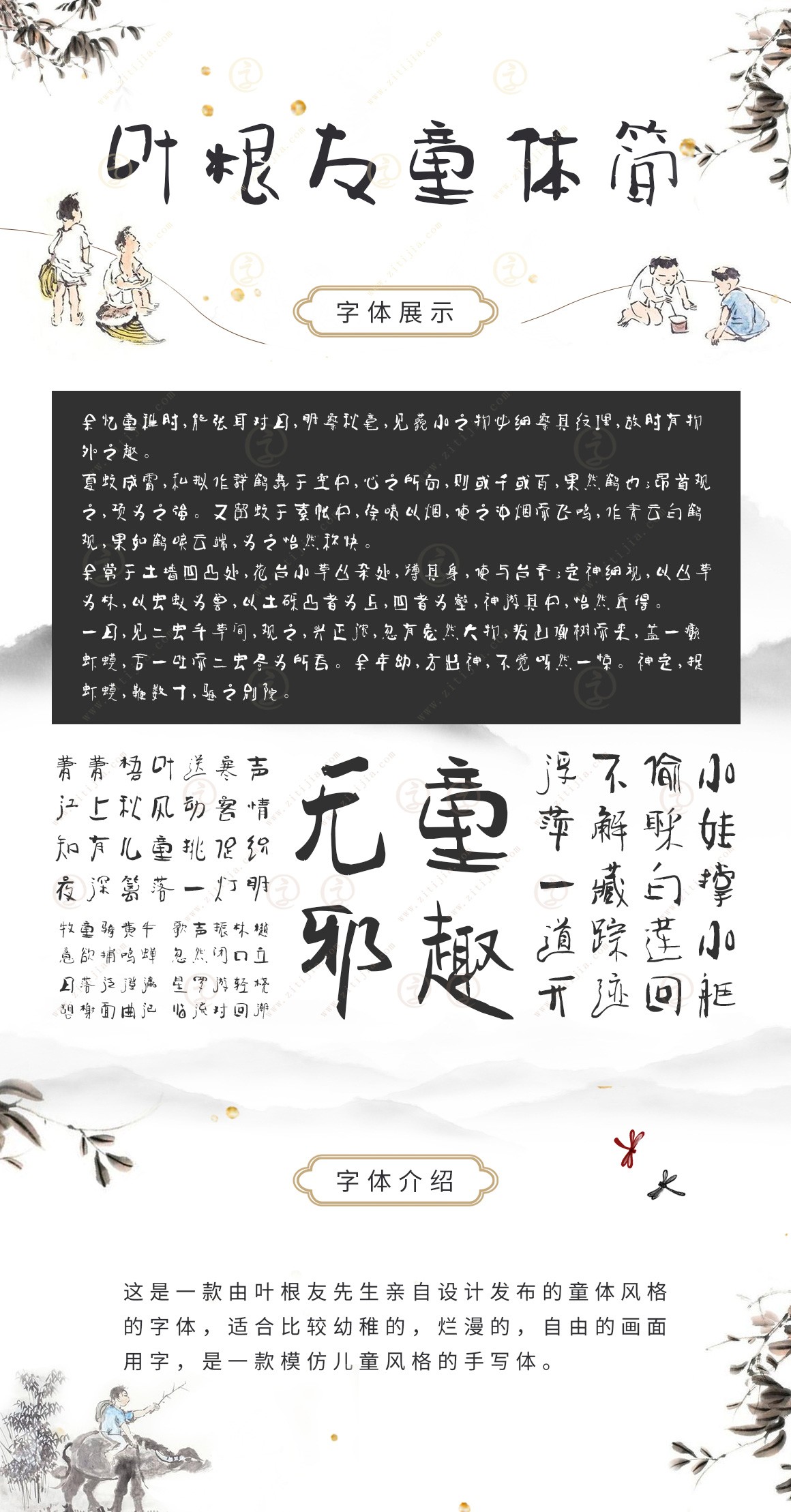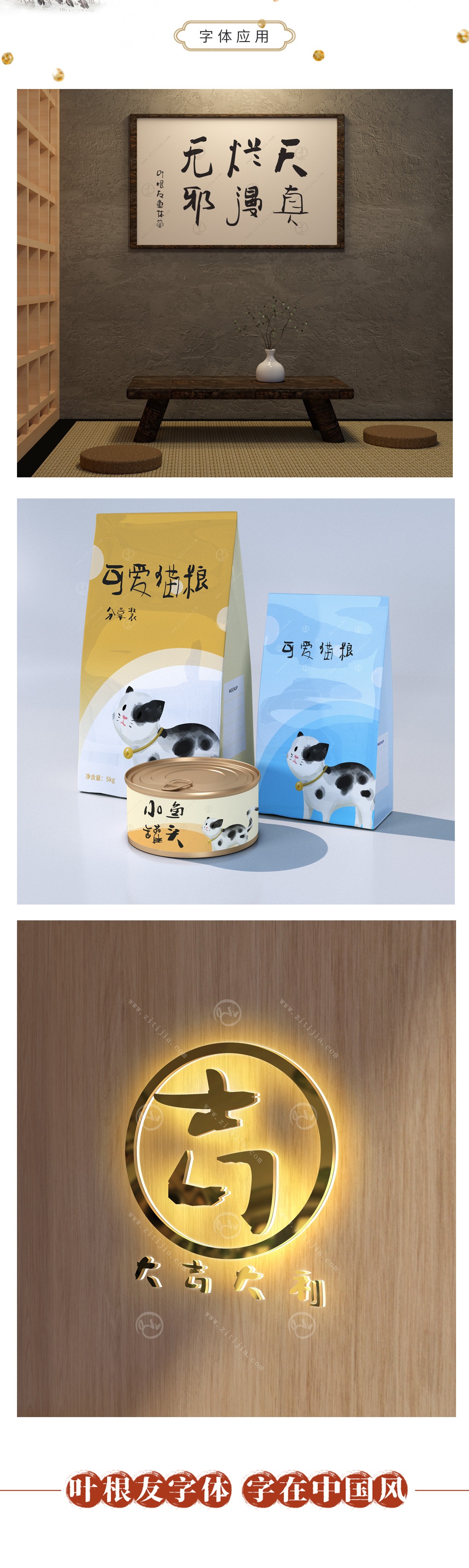
葉根友童體
字體作者:葉根友
創(chuàng)作年代:2009年
字體字?jǐn)?shù):6763個(gè)中文漢字以及其他英文字母和阿拉伯?dāng)?shù)字
字體介紹
葉根友童體字體是刻意地去模仿小學(xué)生的書(shū)寫筆法,靈感來(lái)自于某次的看到小學(xué)生作業(yè)本上的一行字,字看上去雖不整齊,但是有書(shū)卷氣歷存其中,葉根友童體在創(chuàng)作中筆畫運(yùn)用大膽,與平時(shí)的書(shū)寫結(jié)構(gòu)完全不同,需要對(duì)部首的結(jié)體區(qū)別于書(shū)法的筆法,該字體適合運(yùn)用于兒童海報(bào)和一些輕松自由的主題設(shè)計(jì)類標(biāo)題用字。